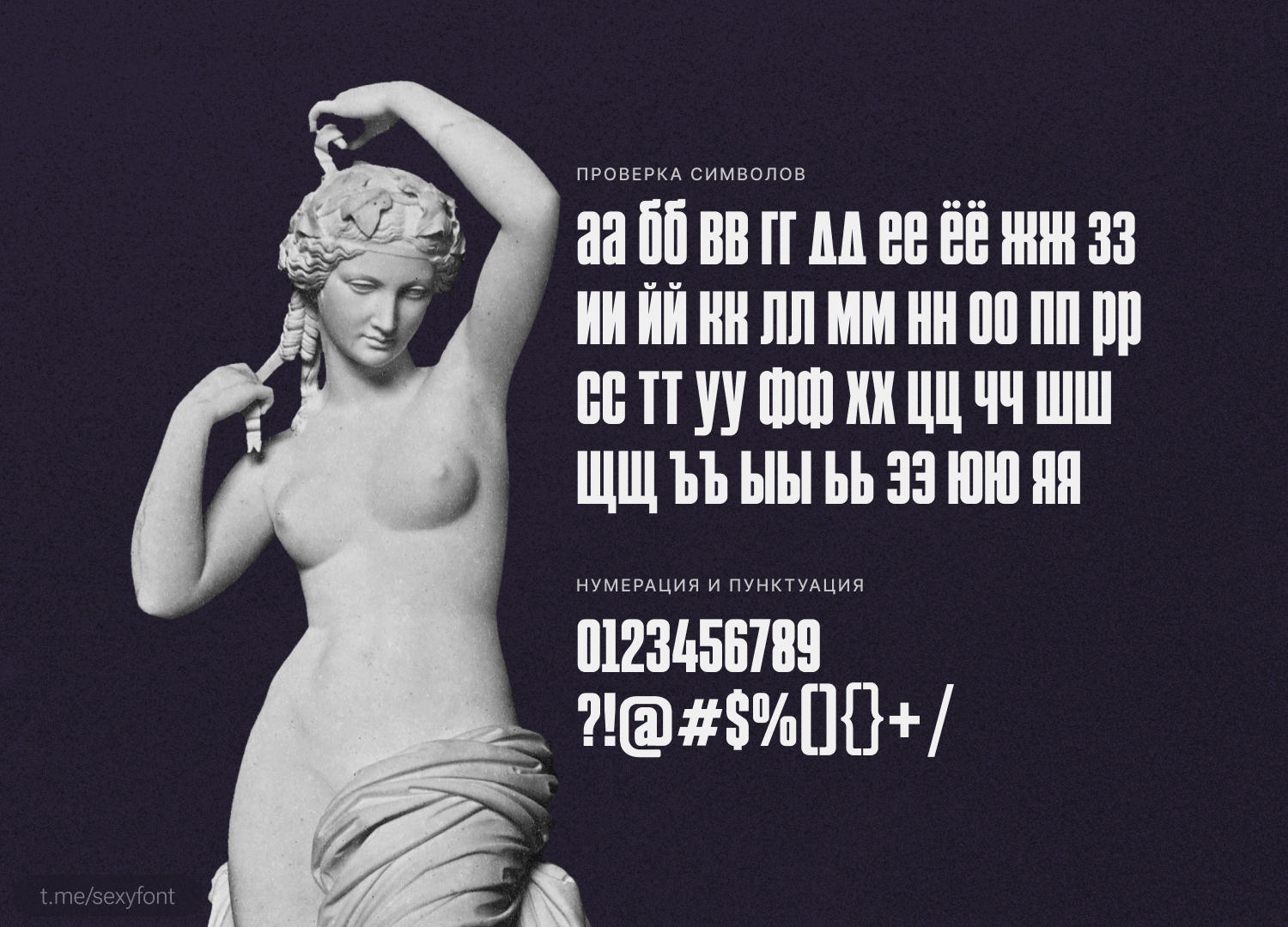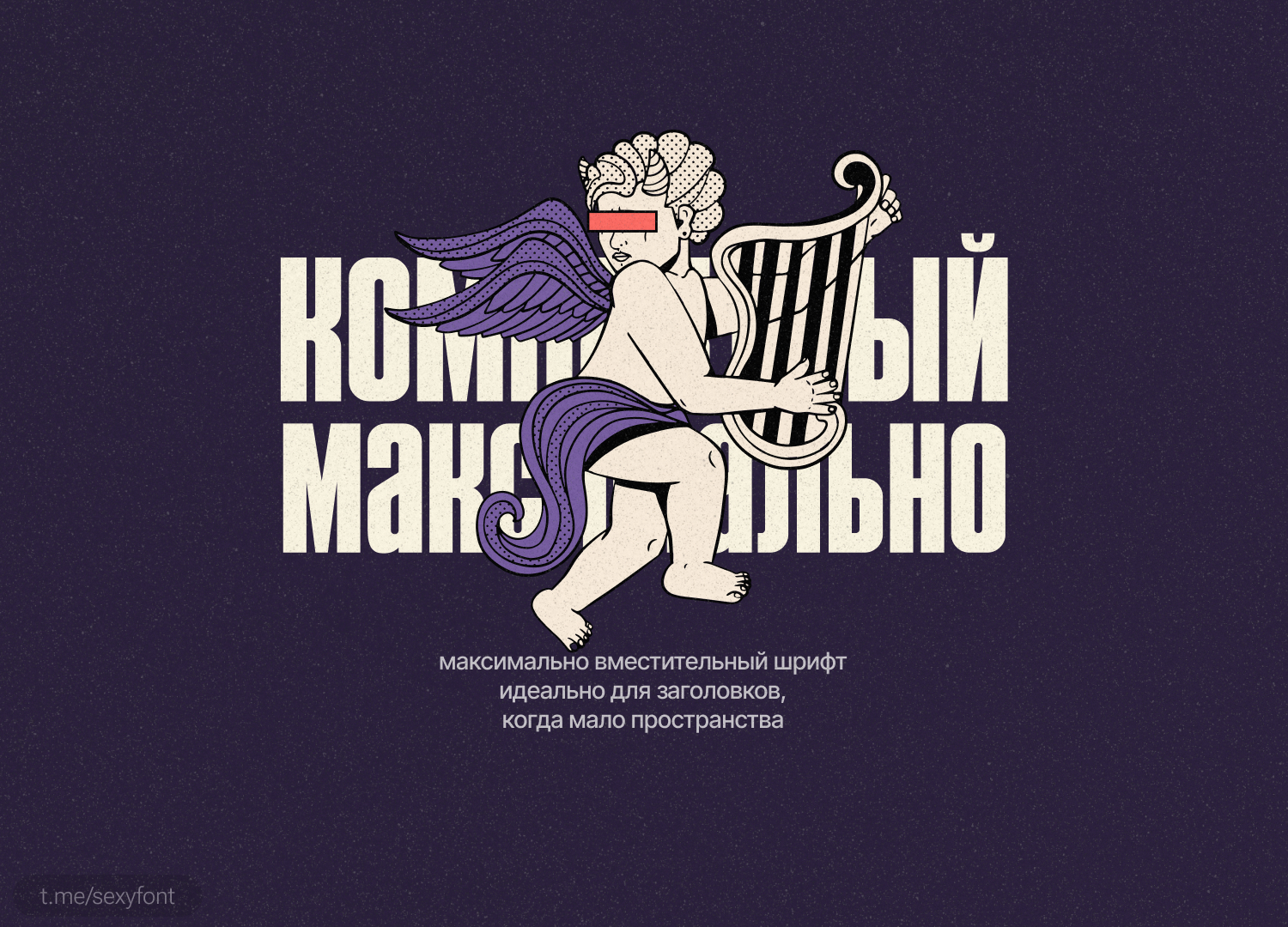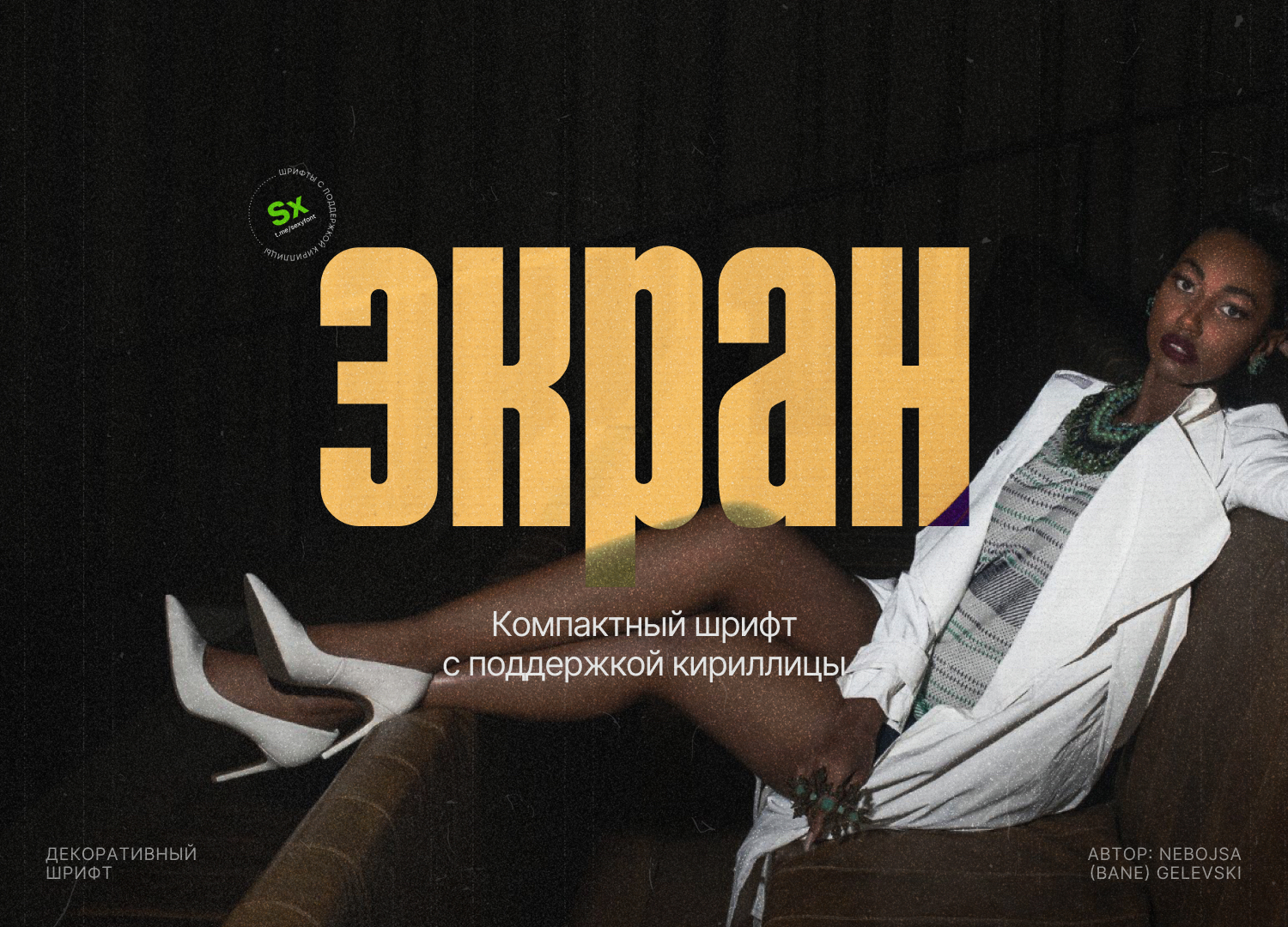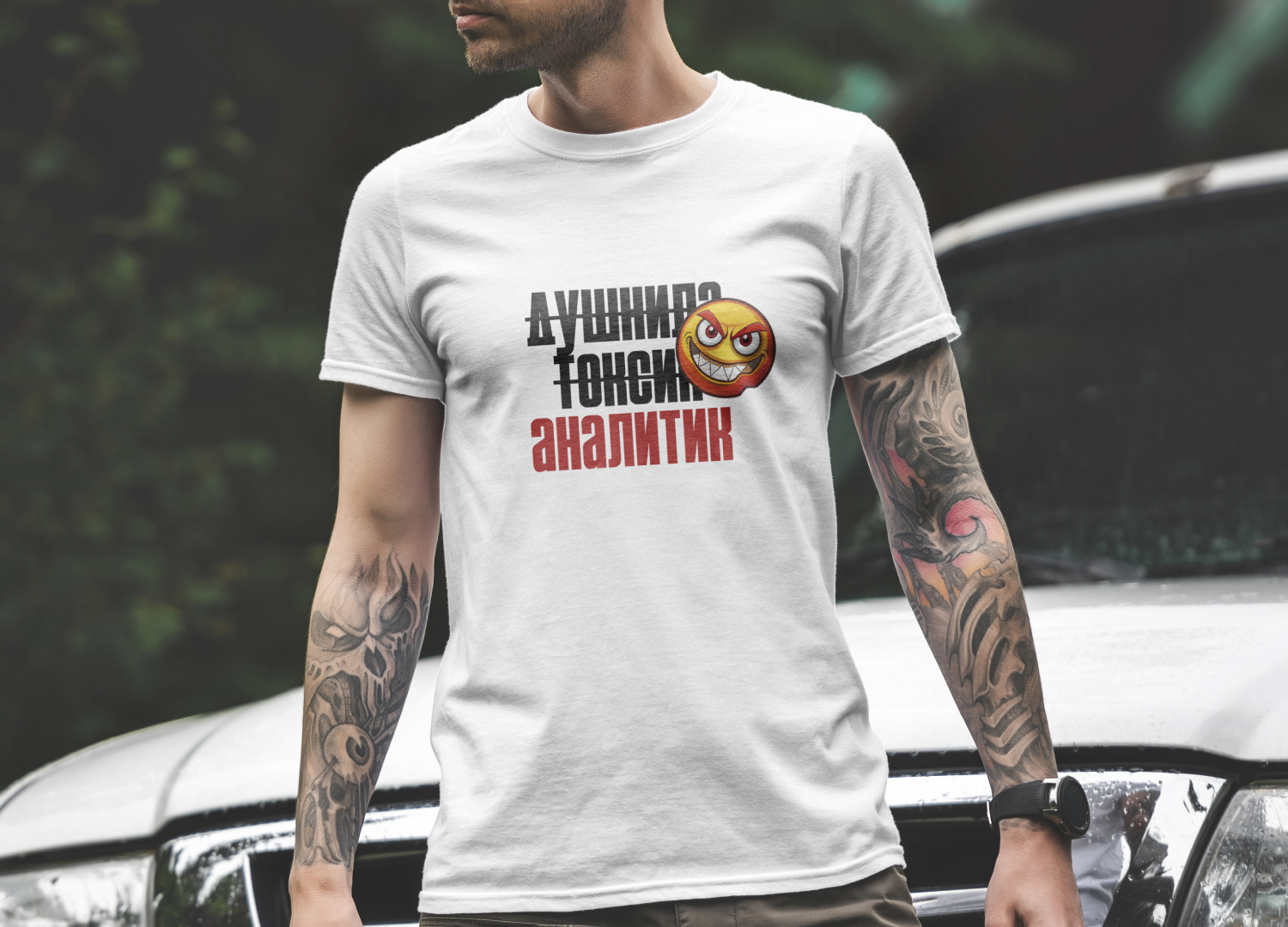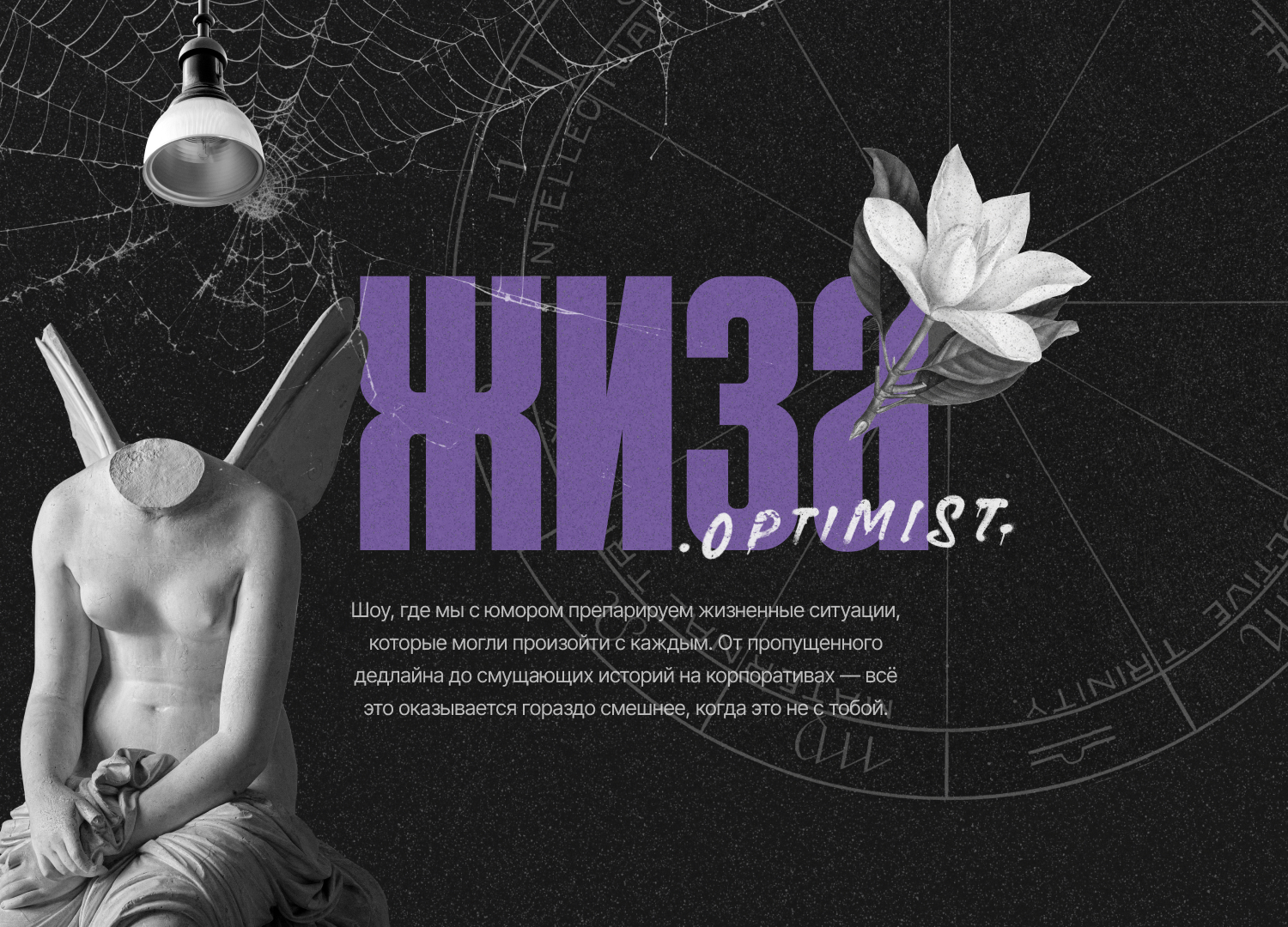
Шрифт Экран
Шрифт Экран. Компактный и вместительный шрифт. Таких не так много) В меру читаемый, но использовать лучше в крупных заголовках. «Экран» черпает вдохновение из заголовочных шрифтов, использовавшихся в македонском еженедельном журнале «Экран» 1970-х годов.